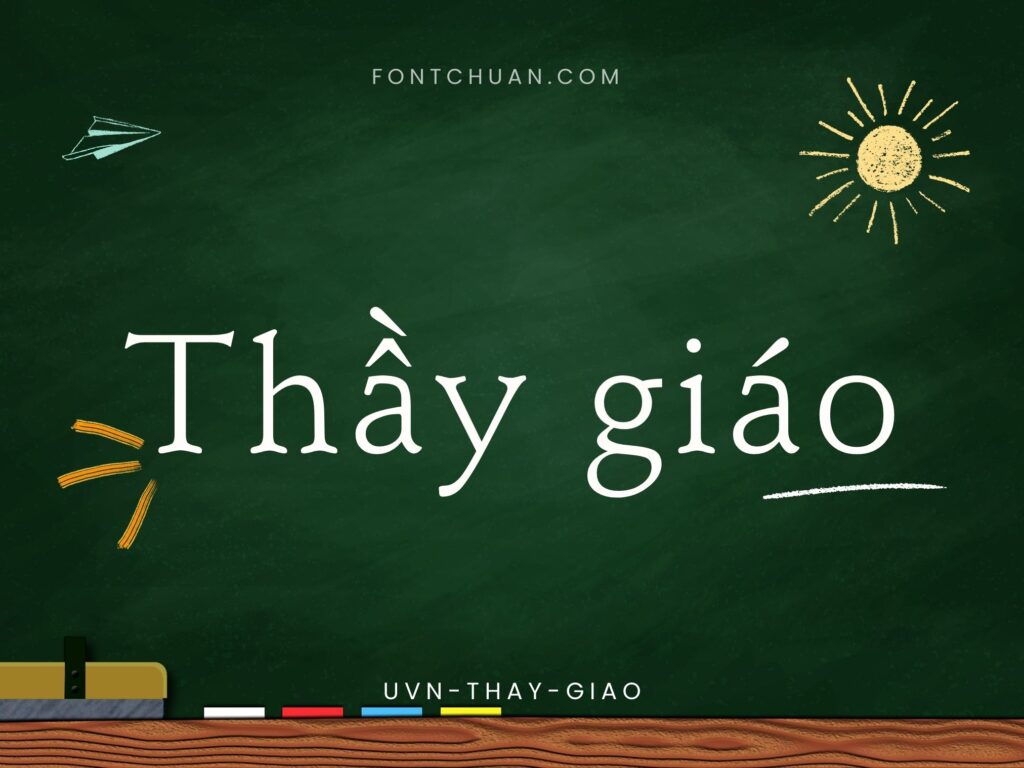
Font UVN Thay Giao Việt Hóa
UVN Thầy Giáo là một kiểu chữ serif truyền thống được thiết kế với các đường nét nghiêm trang và chỉn chu, gợi nhớ đến phong cách chữ in trong sách giáo khoa xưa. Font này chỉ được sưu tầm và đăng bởi thành viên của Font Chuẩn.
UVN Thầy Giáo có cấu trúc chữ rõ ràng, với chân chữ sắc nét, độ đậm vừa phải, giúp tăng khả năng đọc ở mọi kích thước. Font này rất phù hợp trong thiết kế sách giáo trình, tiêu đề cho các bài giảng, tài liệu học tập và ấn phẩm học thuật. Các ngành nghề như giáo dục, quảng cáo, công nghệ và bất động sản đều có thể sử dụng UVN Thầy Giáo để truyền tải nội dung một cách chuyên nghiệp và dễ tiếp cận.